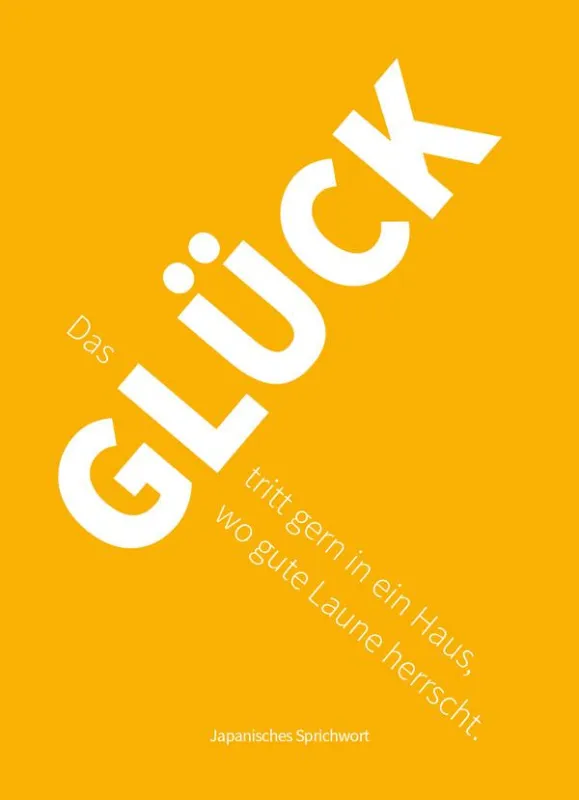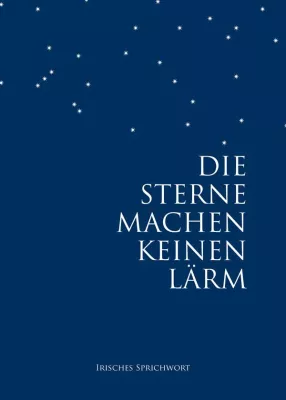
Typografie-Postkarten mit wundervollen Zitaten
Neu: 25 Postkarten-Motive mit aufmunternden Botschaften
(openPR) Bünde, 07.03.2016 – Modern, plakativ und farbenfroh. Neu und einzigartig. Postkarten-Zitate in plakativer Gestaltung.
Zu den Themen Glück, Liebe, Freundschaft, Geburtstag, Mut, Dankbarkeit und Weisheit, bilden „positive Zitate“ und „Aphorismen“ die Grundlage für ein wunderschönes Postkarten-Motiv. Mit diesen Aussagen anderen Menschen Mut machen, sie aufbauen bei Leid, Trost spenden bei Kummer oder einfach eine Freundschaft bekräftigen und das die Liebe, das Glück und der Dank nicht in Vergessenheit geraten. Diese Überlegungen führten zu dieser einzigartigen Gestaltung.
Wortschätze? Verwenden wir zu selten. In einer hektischen Zeit brauchen wir auch Ruhe, Ausgeglichenheit und Zufriedenheit. Themen, auf die wir uns besinnen können. Daraus entstand diese einzigartige Postkartenserie mit wundervollen Wortschätzen.